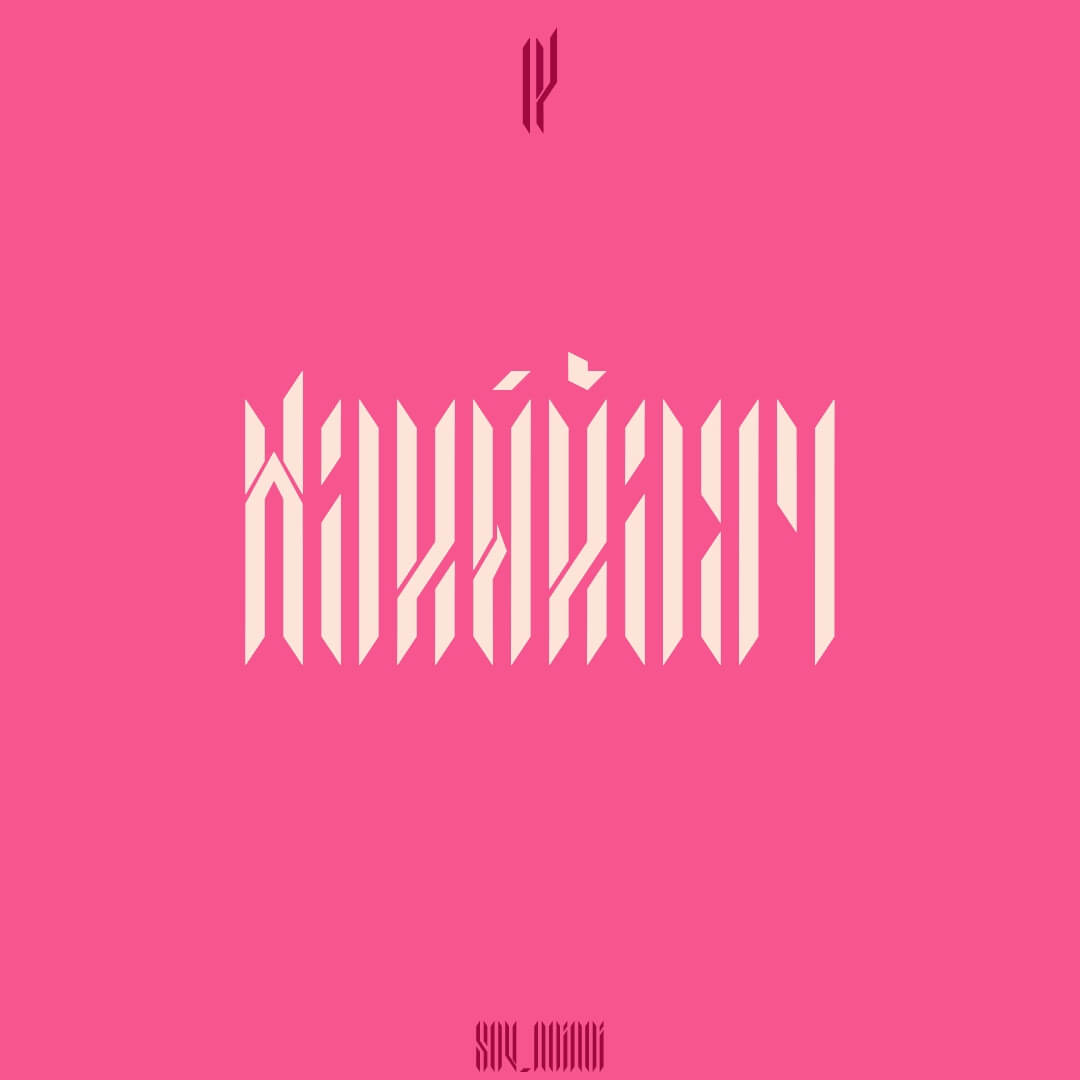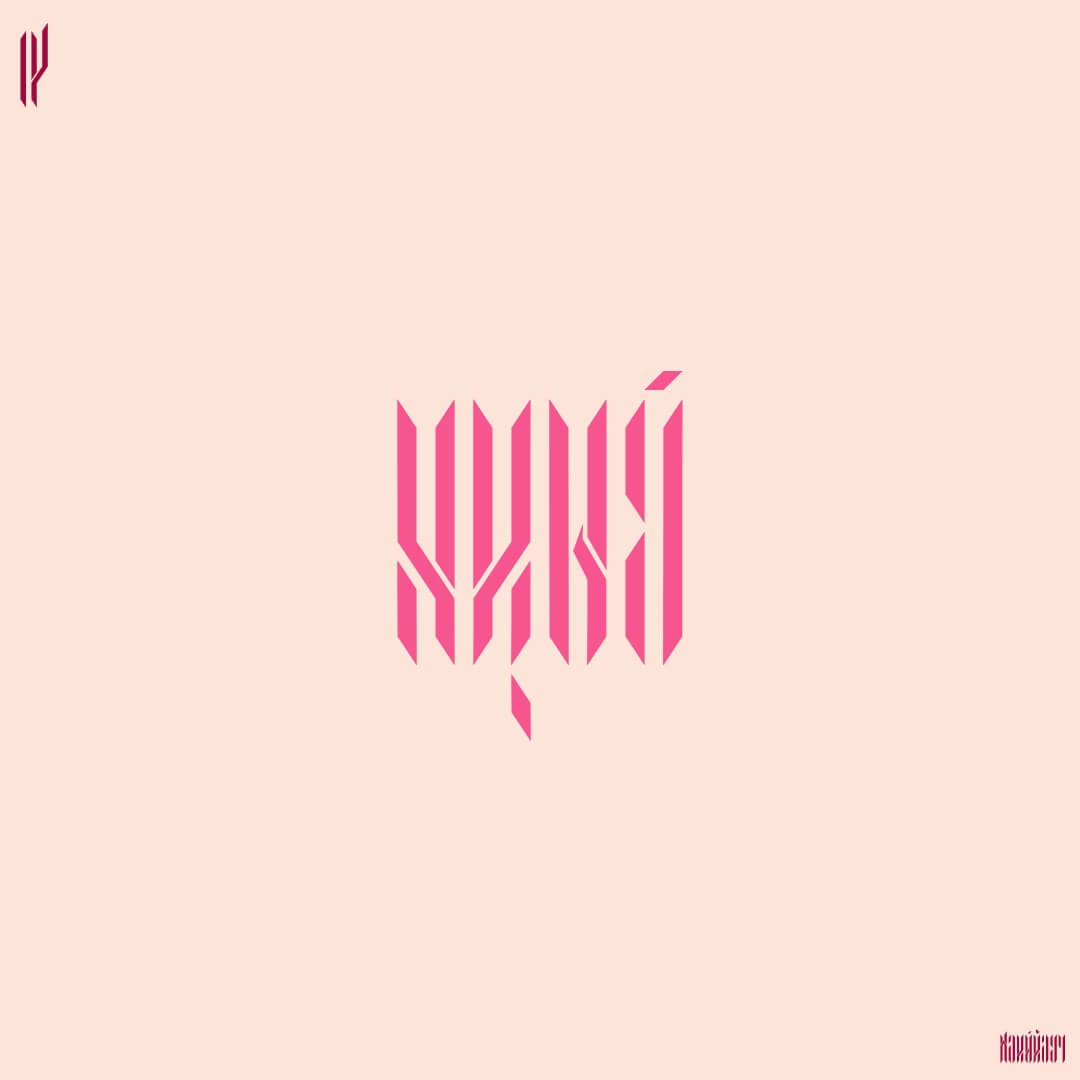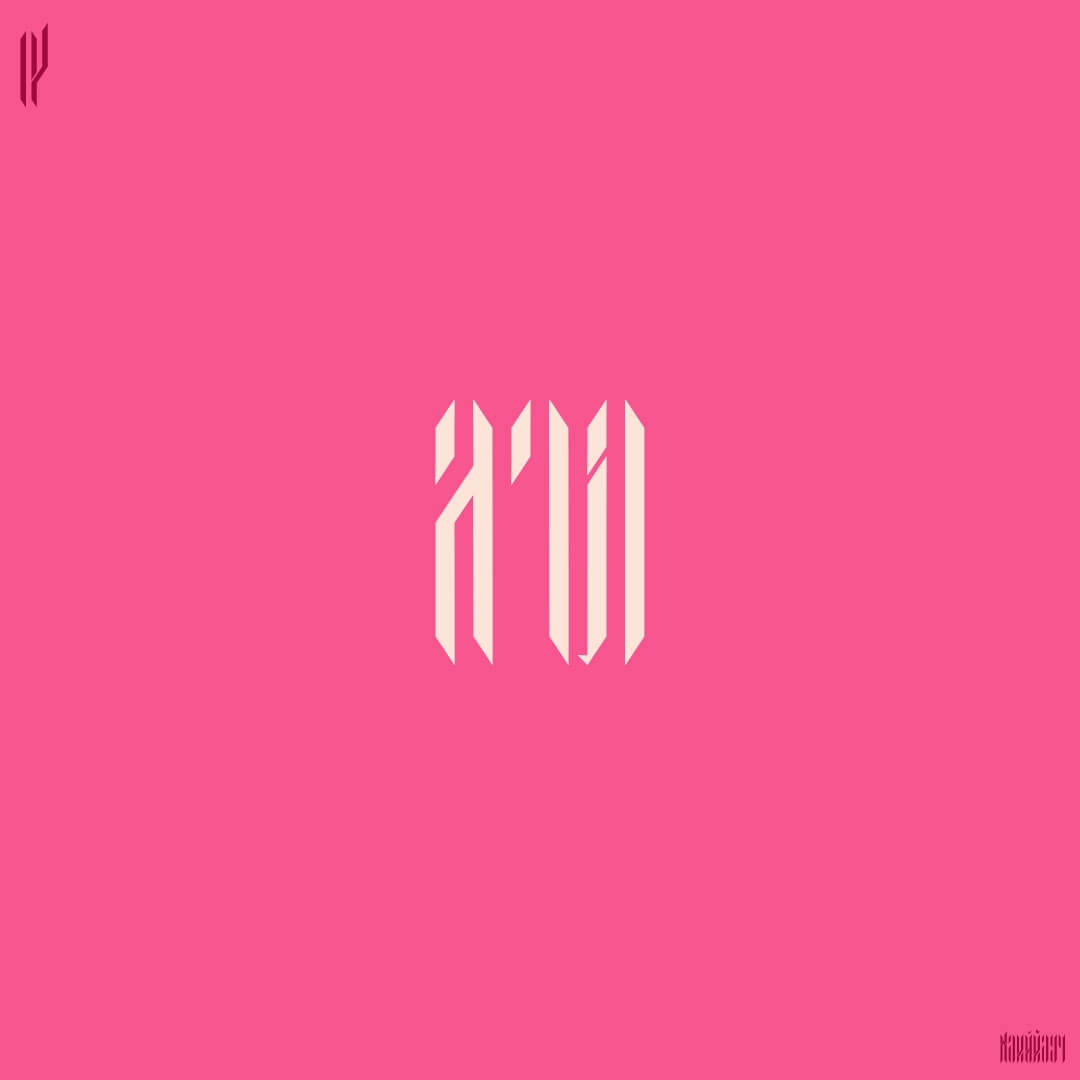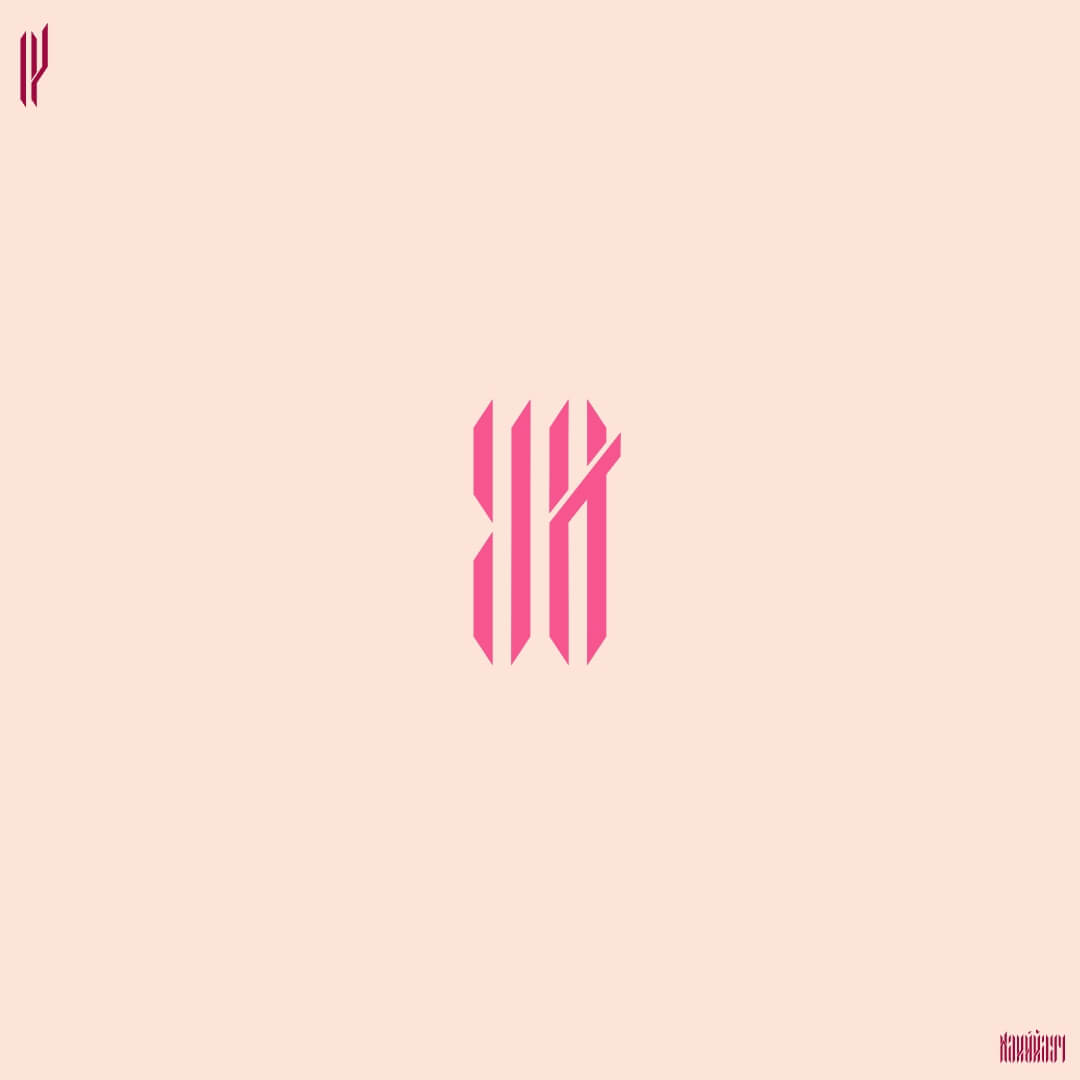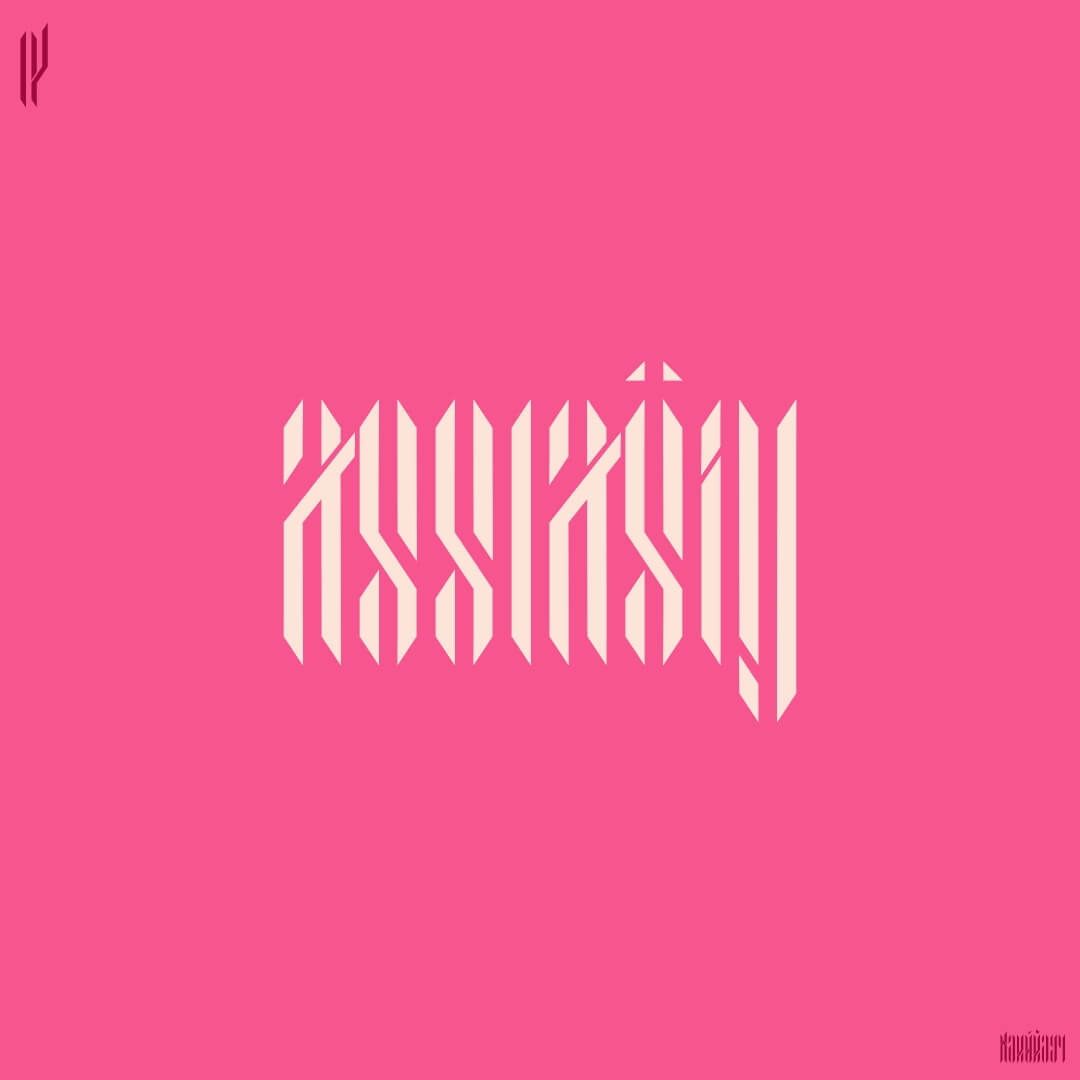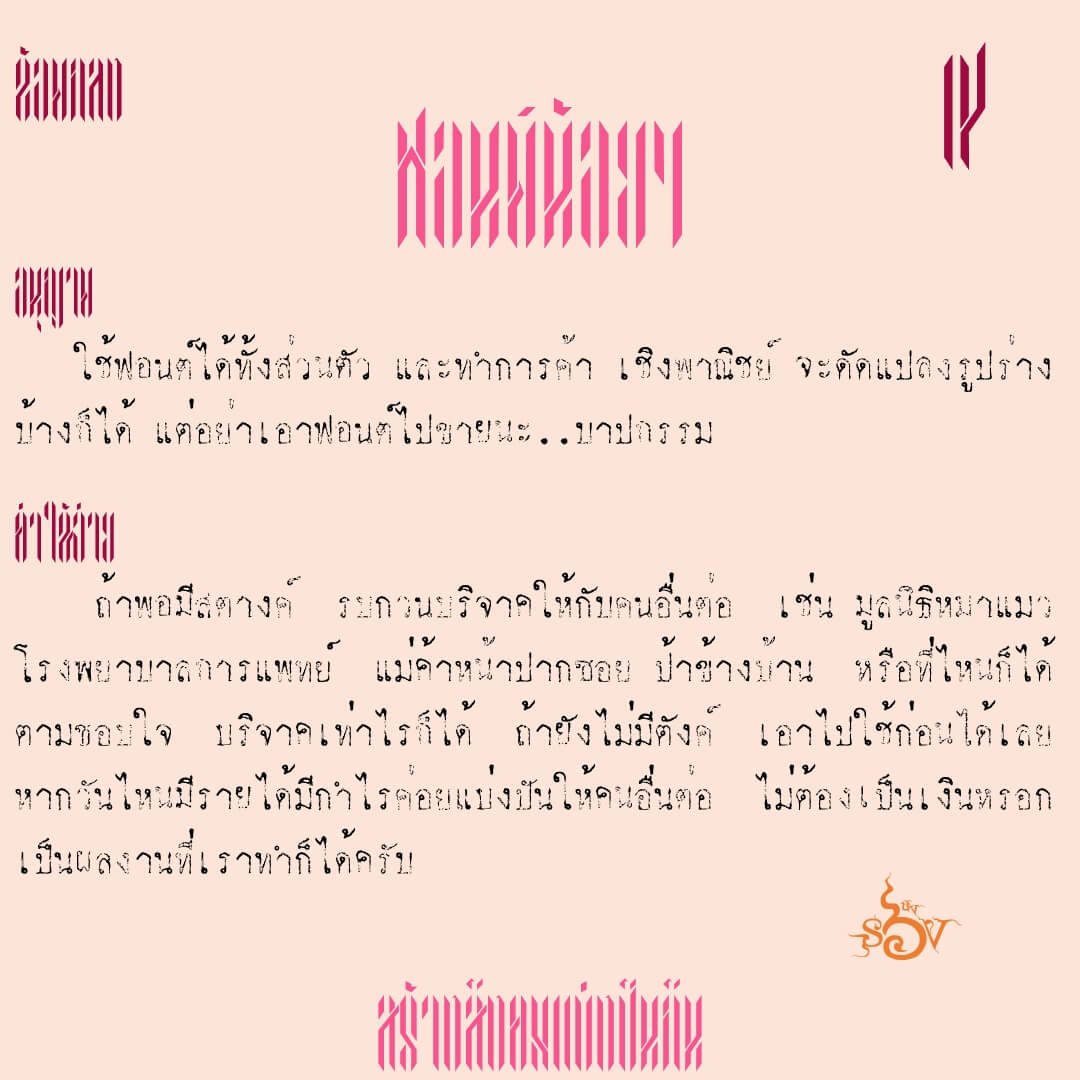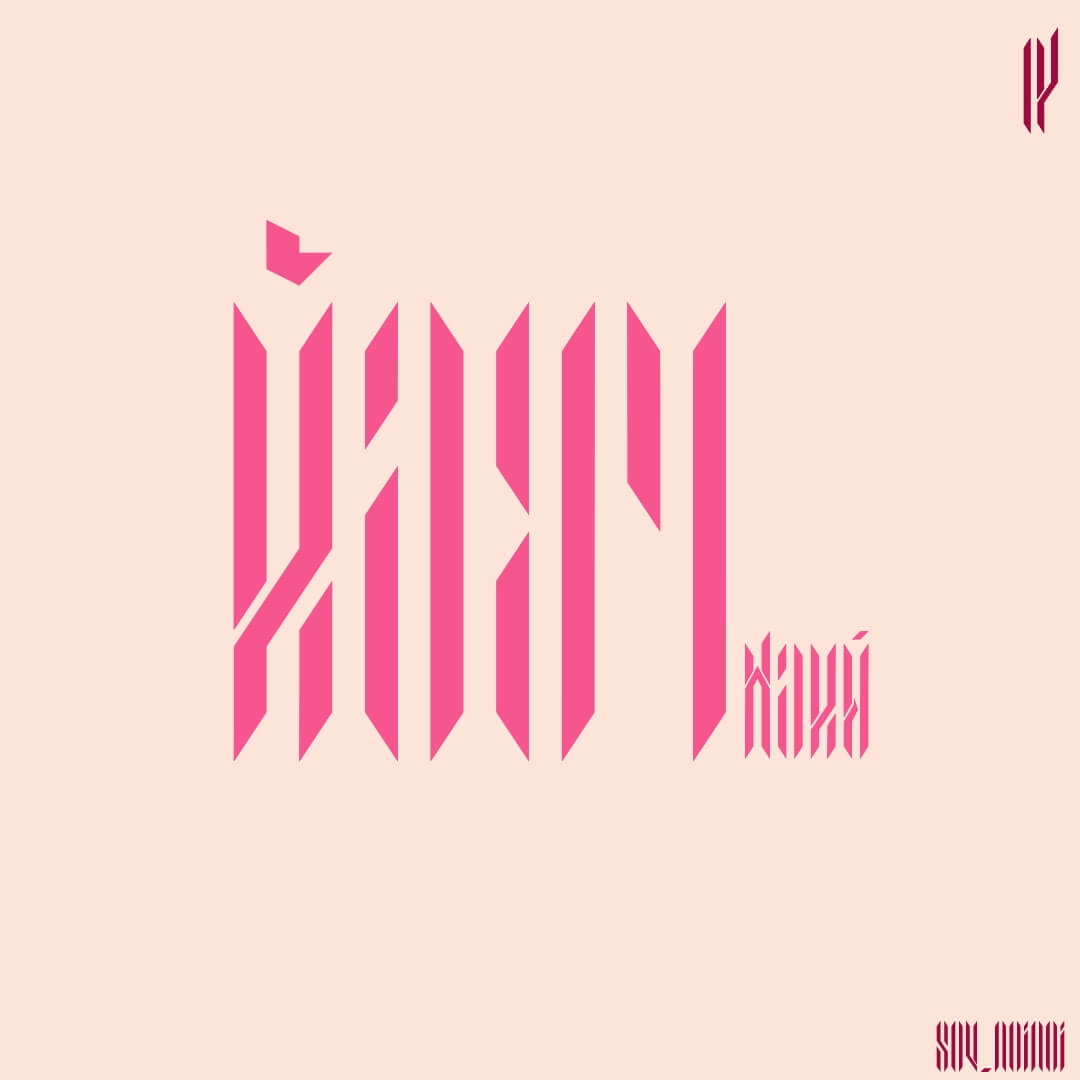
น้อยๆ (SOV_NoiNoi)
ฟอนต์น้อยๆ – เป็น logo font ตัวอักษรน้อยๆ แนะนำไม่เกิน 5 ตัวอักษร เพราะตาเราจะเริ่มแยกแยะไม่ออกแล้ว
เบื้องหลังการออกแบบ : ฟอนต์ น้อยๆ